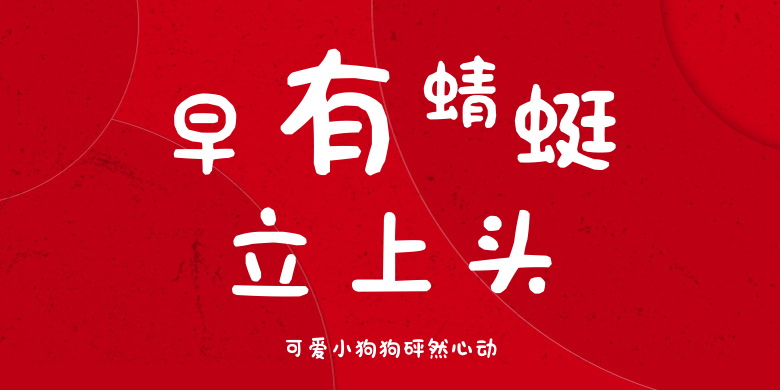
可爱小狗狗砰然心动
可爱小狗狗砰然心动,这款字体结构工整、笔画清晰,兼顾美观与易读性,适用于标题、正文、海报、包装、LOGO 等多种场景。字形优雅稳定,风格百搭耐看,适配日常排版与创意设计,让文字呈现更舒适、更具质感。可爱小狗狗砰然心动一笔一画,皆是细节,以均衡的比例、流畅的线条打造舒适视觉体验,字形端正大气,风格简约现代。无论是商业设计、品牌宣传还是日常排版,都能轻松驾驭,让文字更有格调与力量。可爱小狗狗砰然心动字体下载。